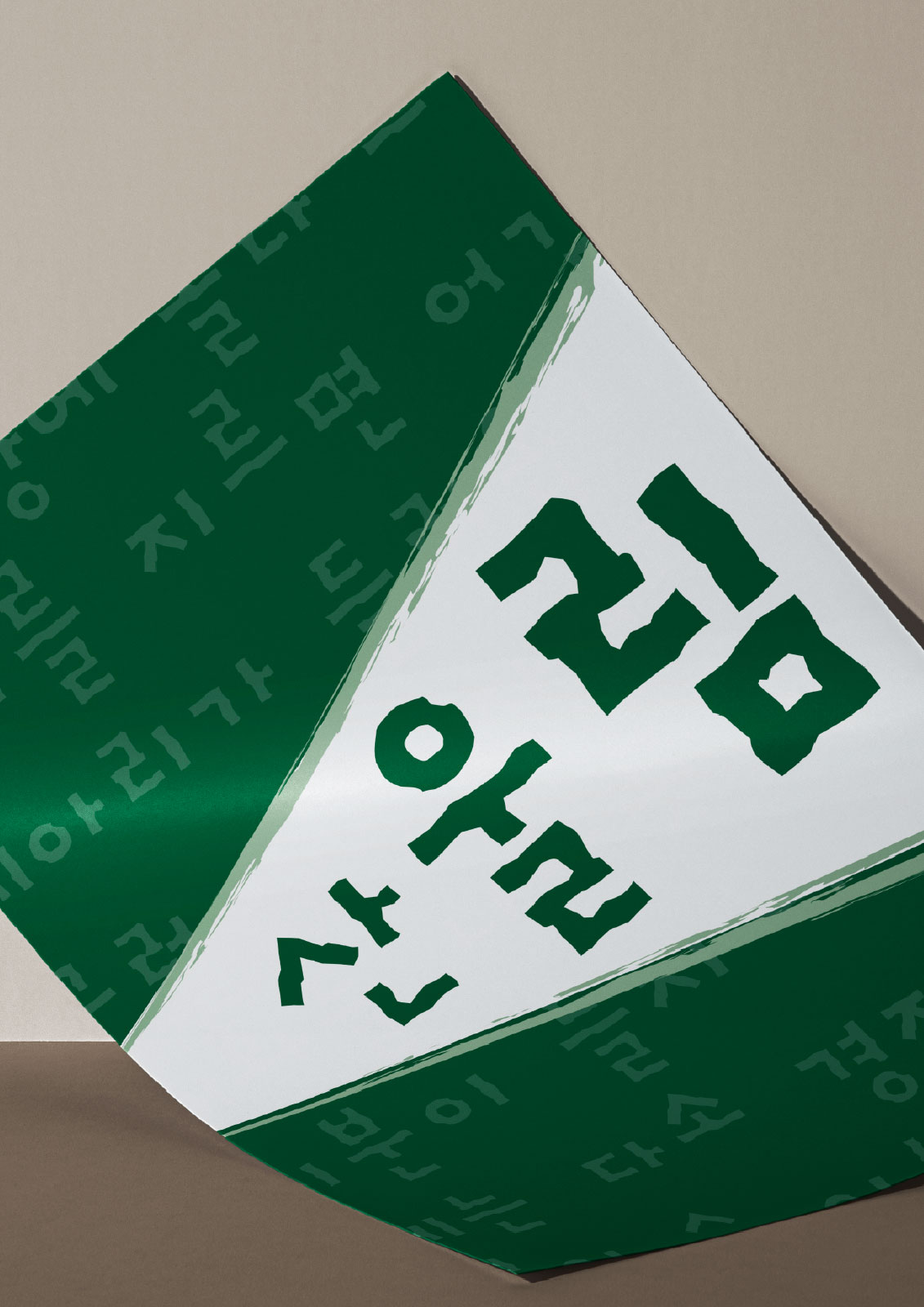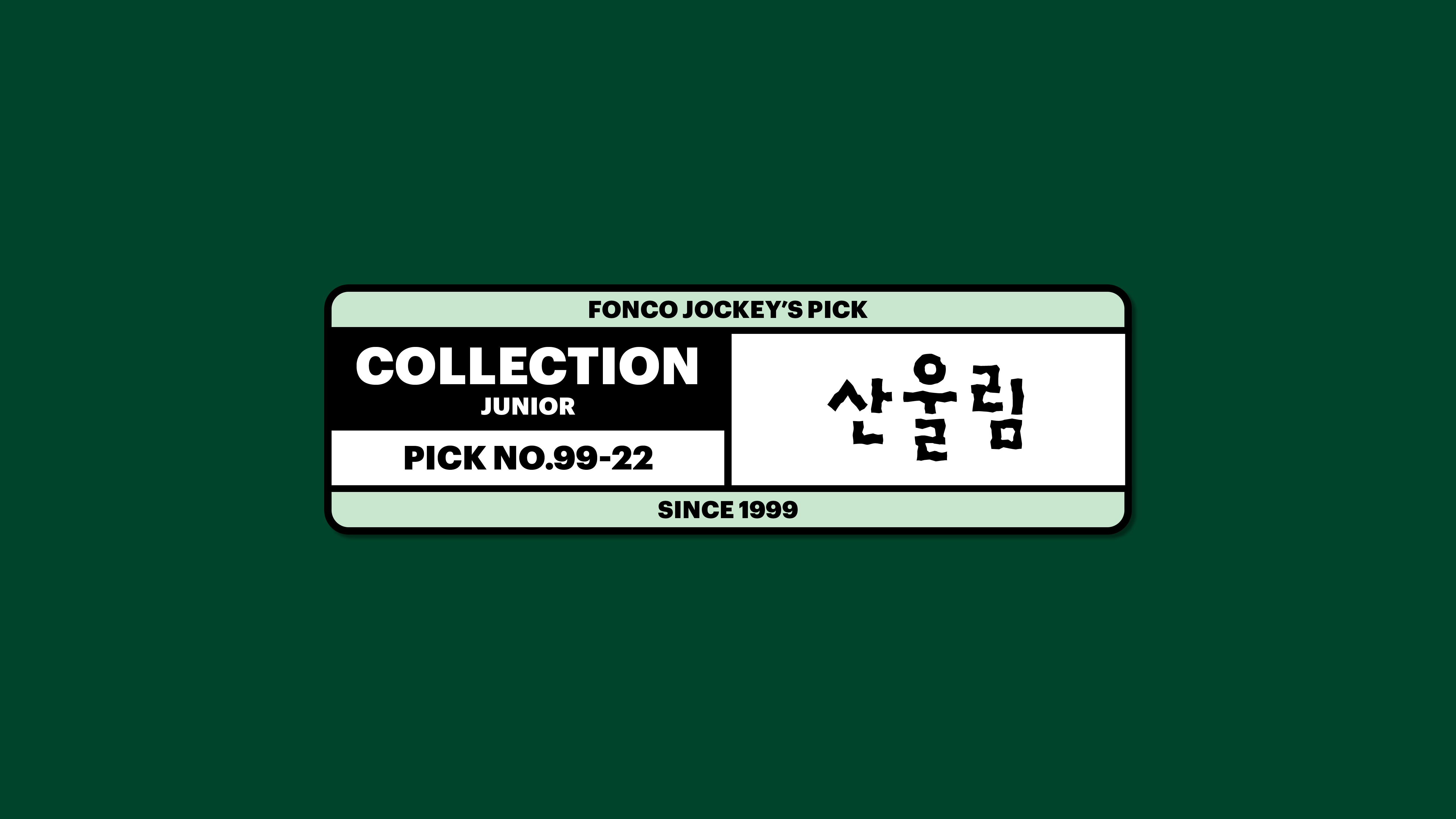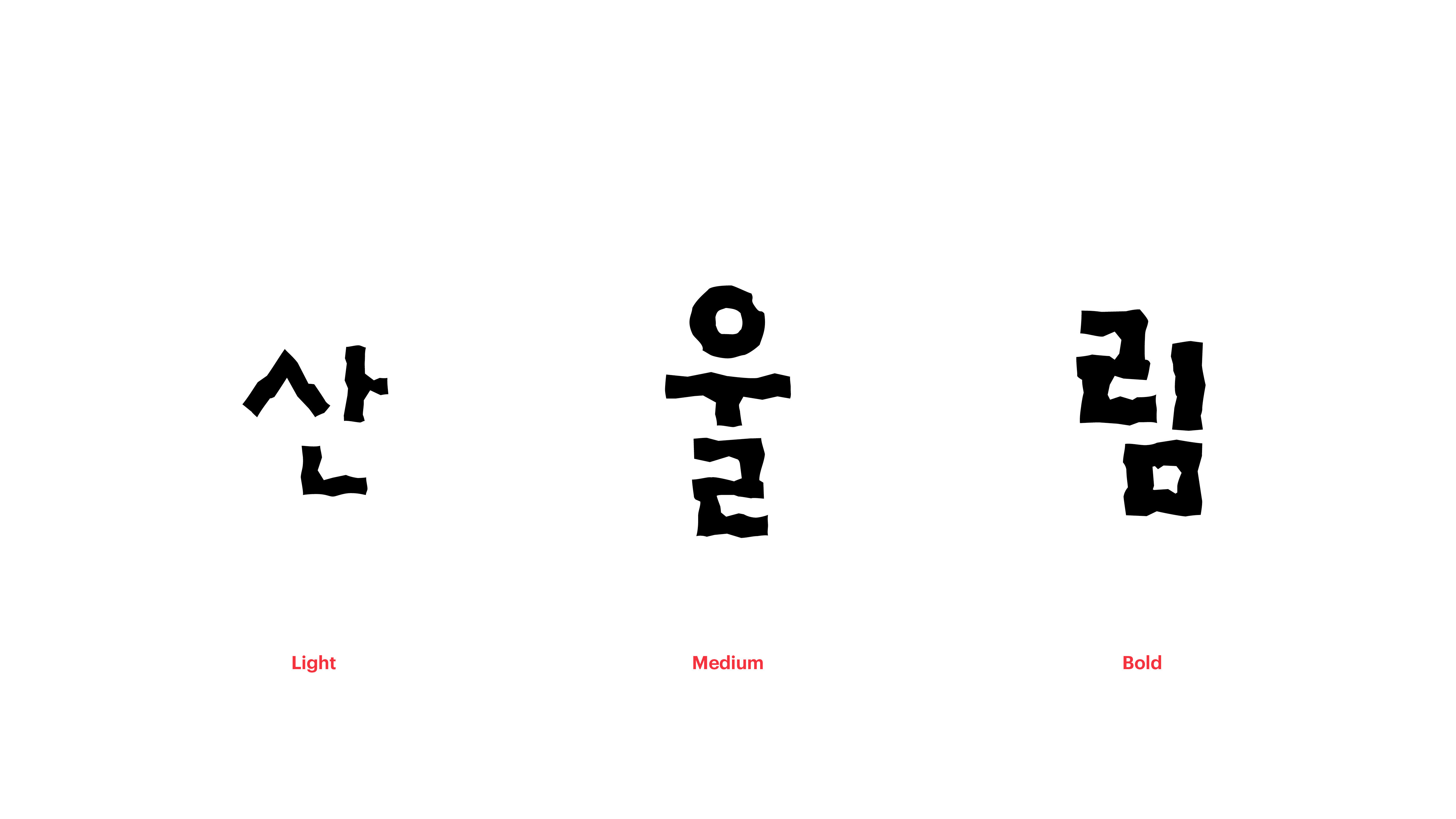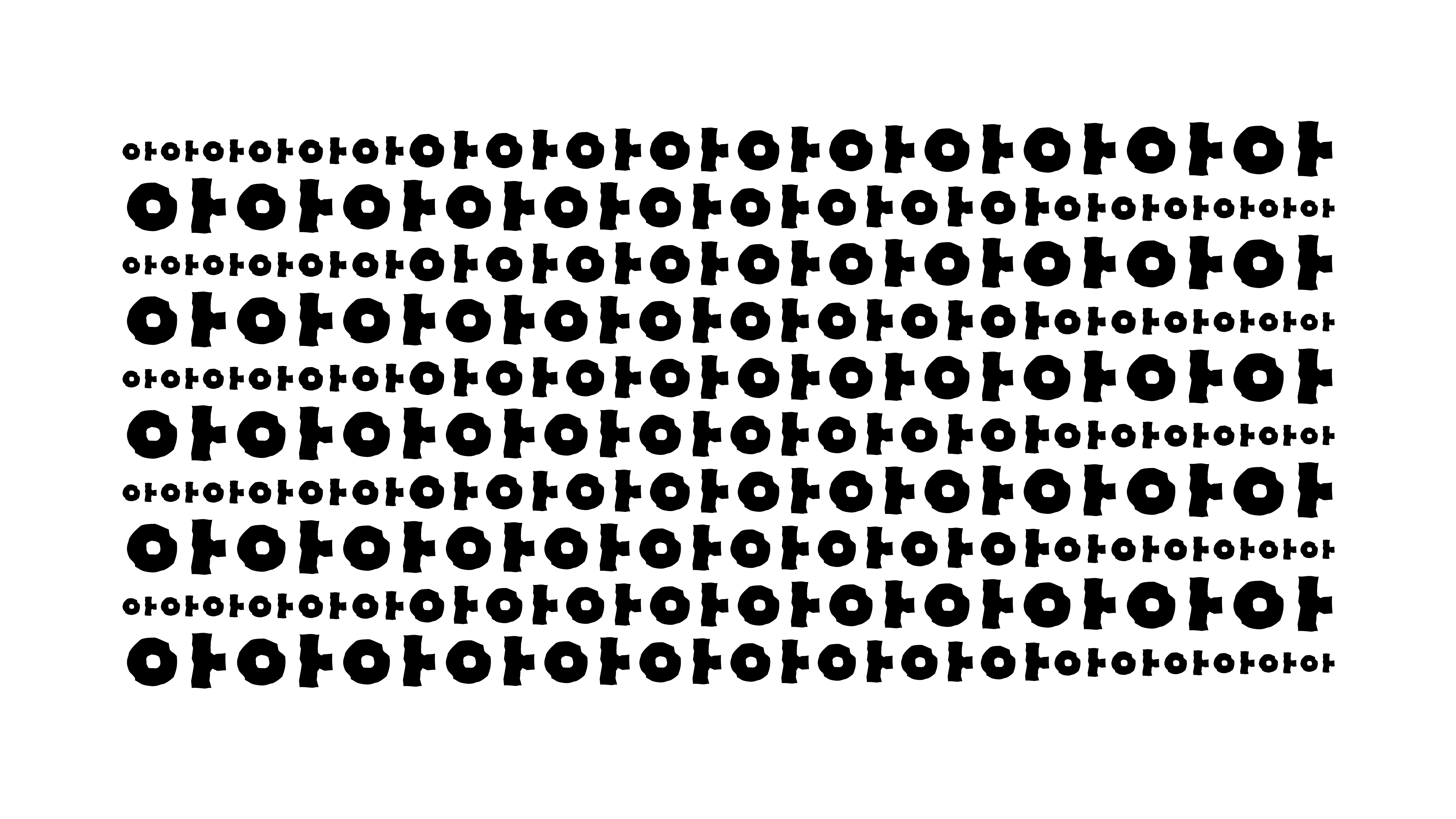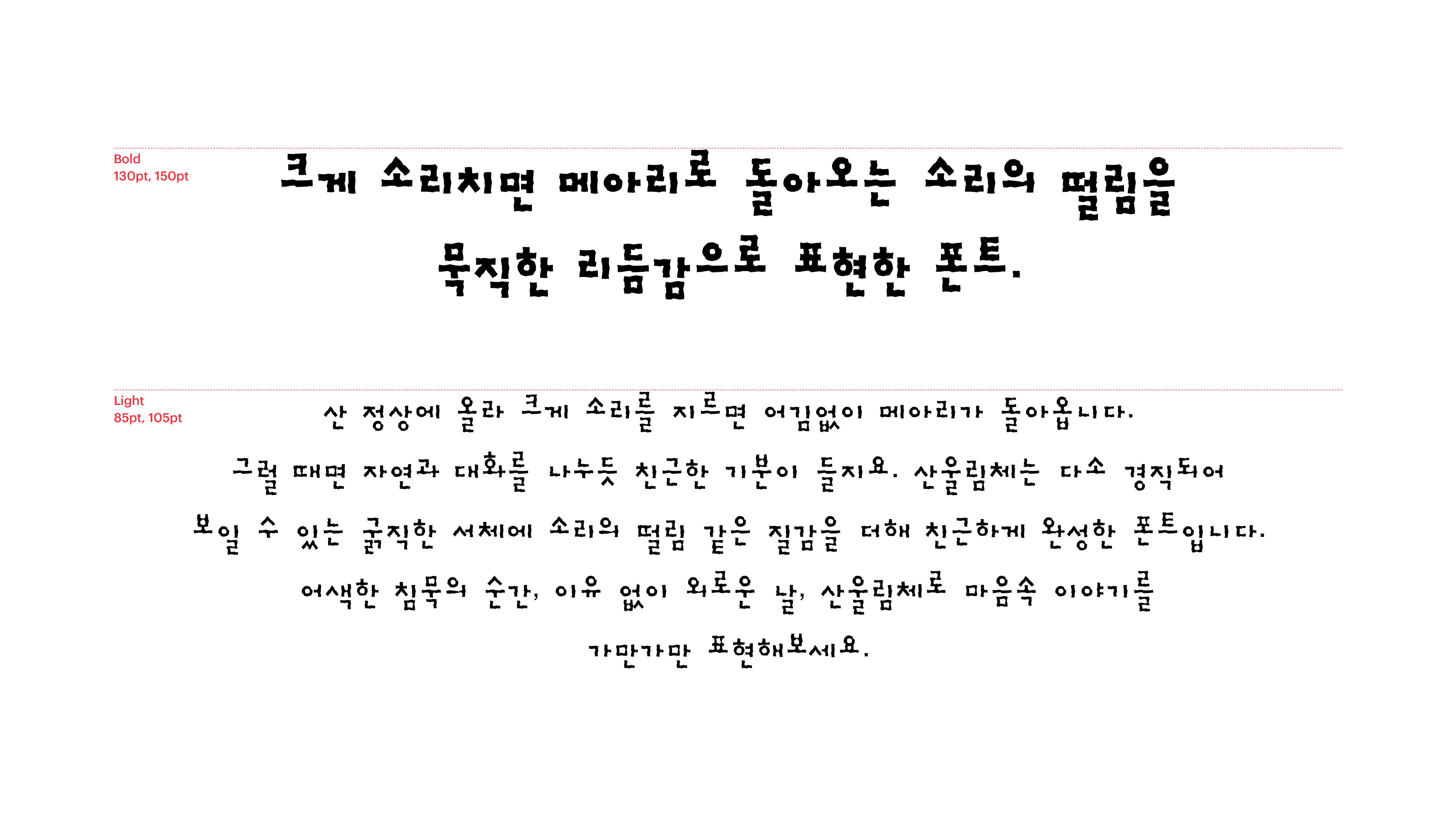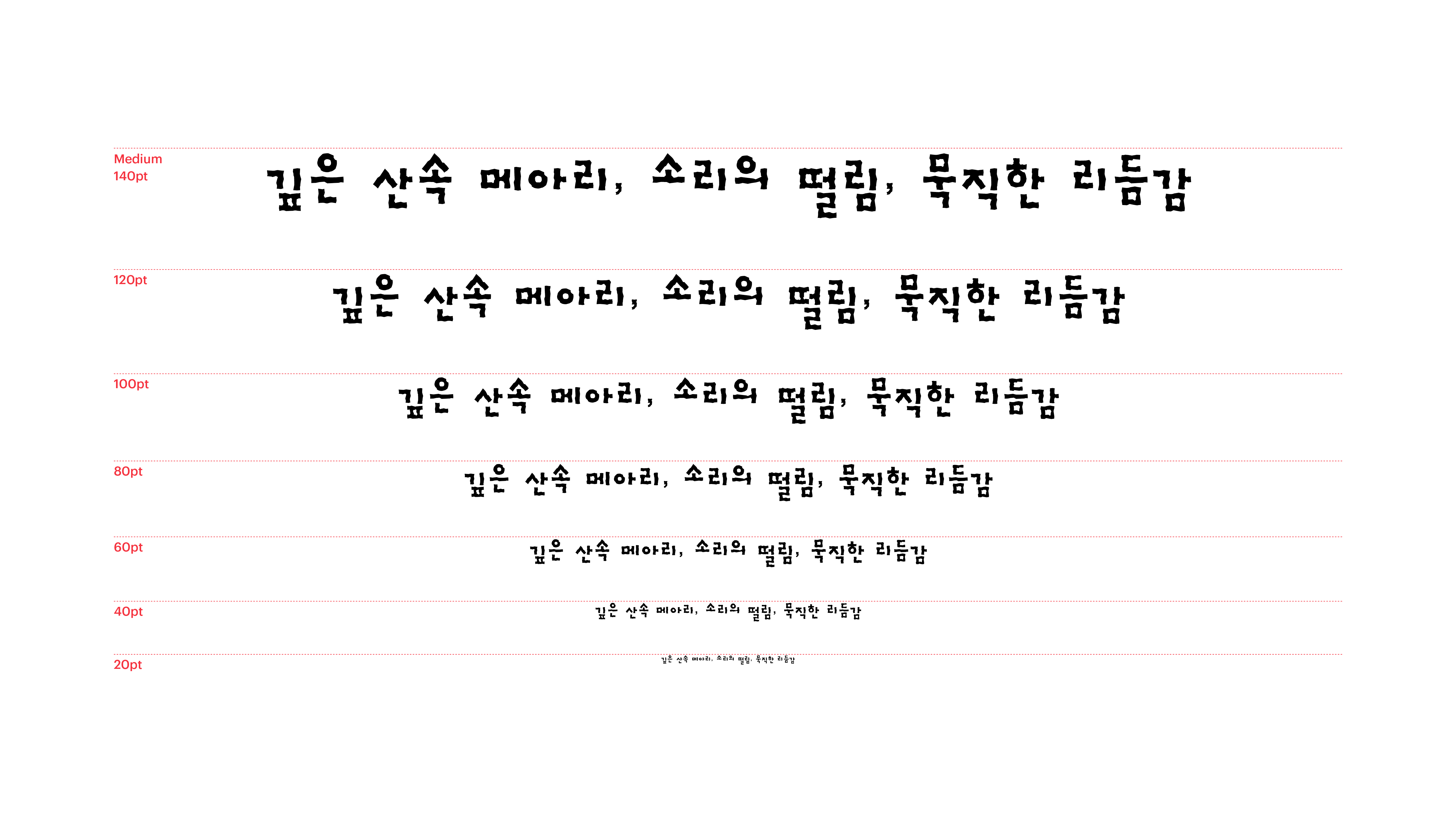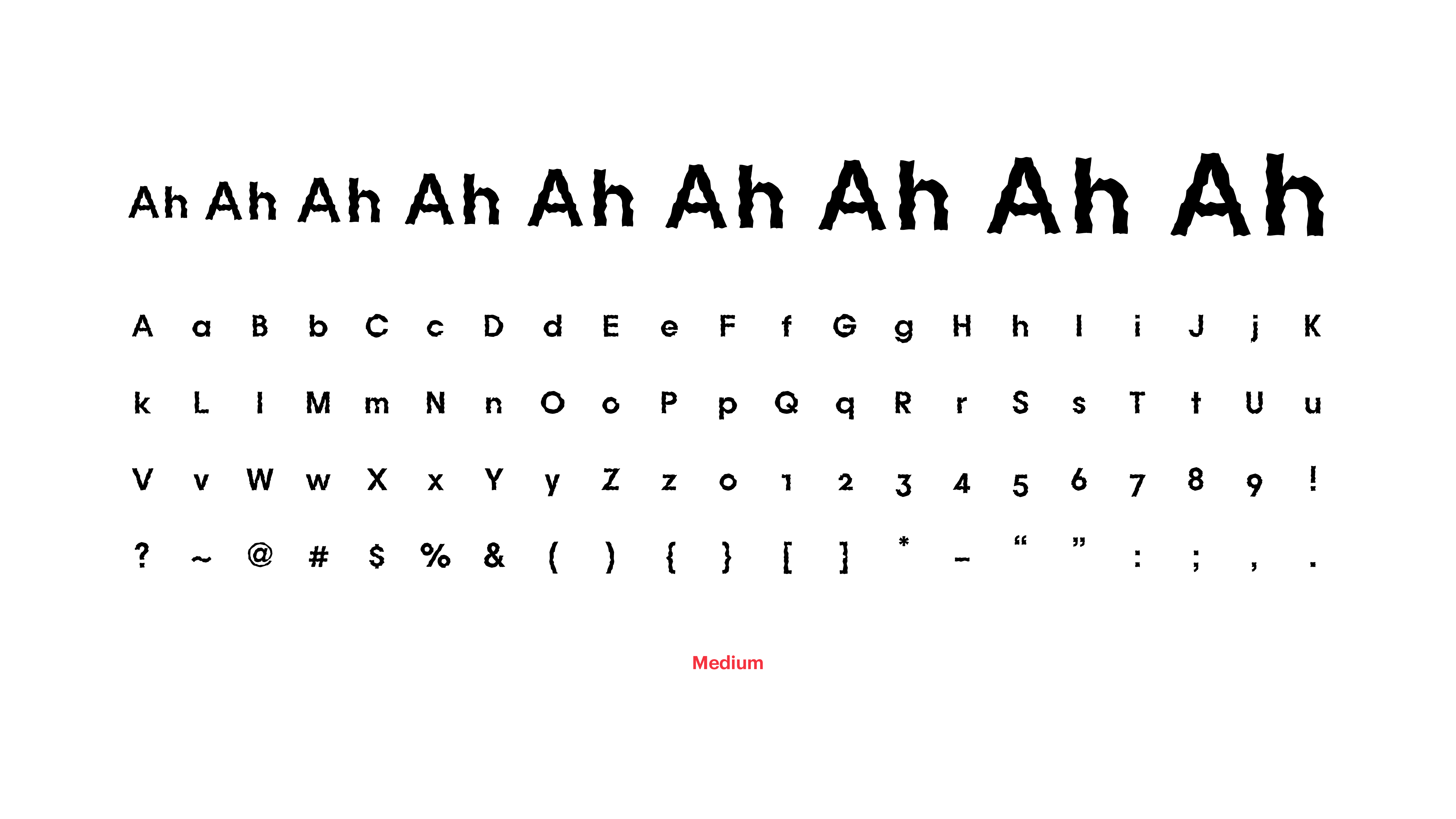
산 정상에 올라 크게 소리를 지르면 어김없이 메아리가 들려옵니다. 그럴 때면 자연과 대화를 나누듯 친근한 기분이 들지요. 산울림체는 다소 경직되어 보일 수 있는 굵직한 서체에 소리의 떨림 같은 질감을 더해 친근하게 완성한 폰트입니다. 어색한 침묵의 순간, 이유 없이 외로운 날, 산울림체로 마음속 이야기를 가만가만 표현해보세요.
Yoon 산울림